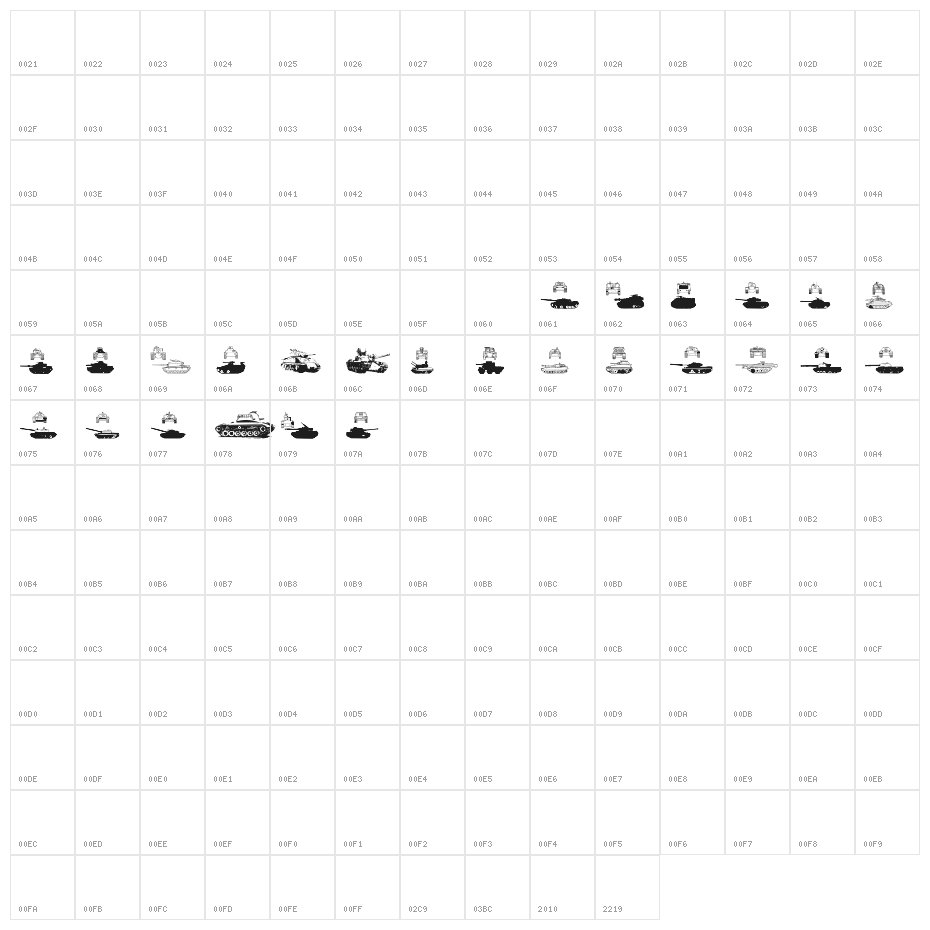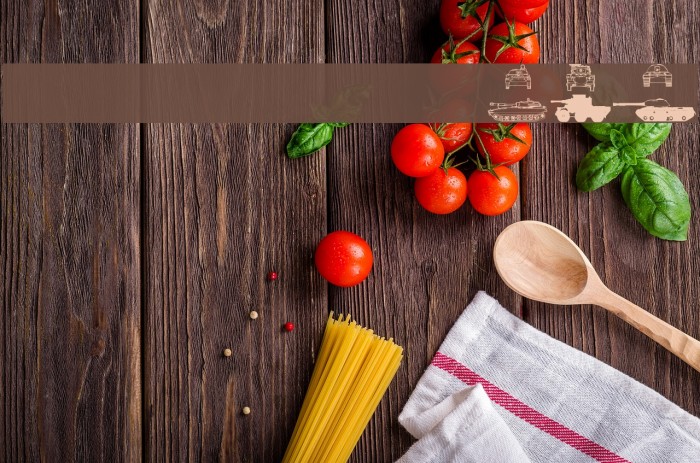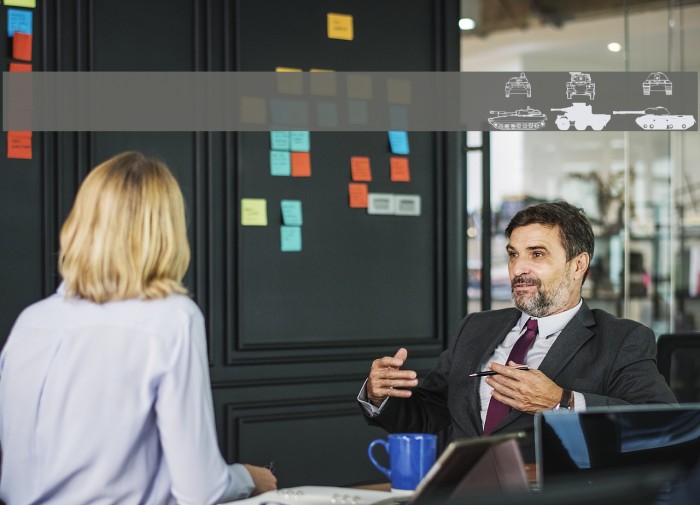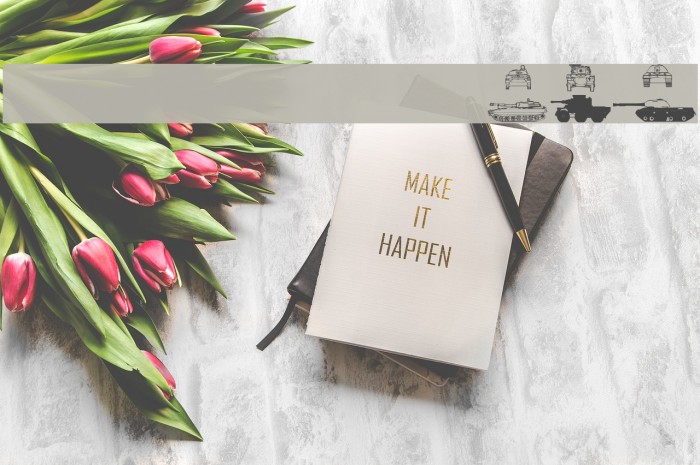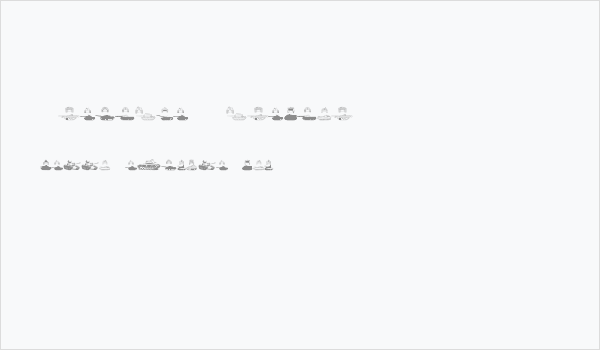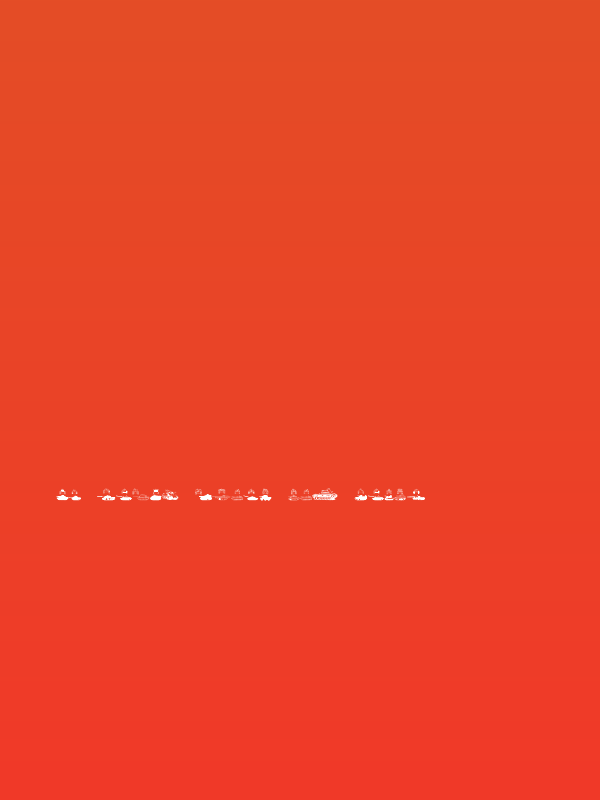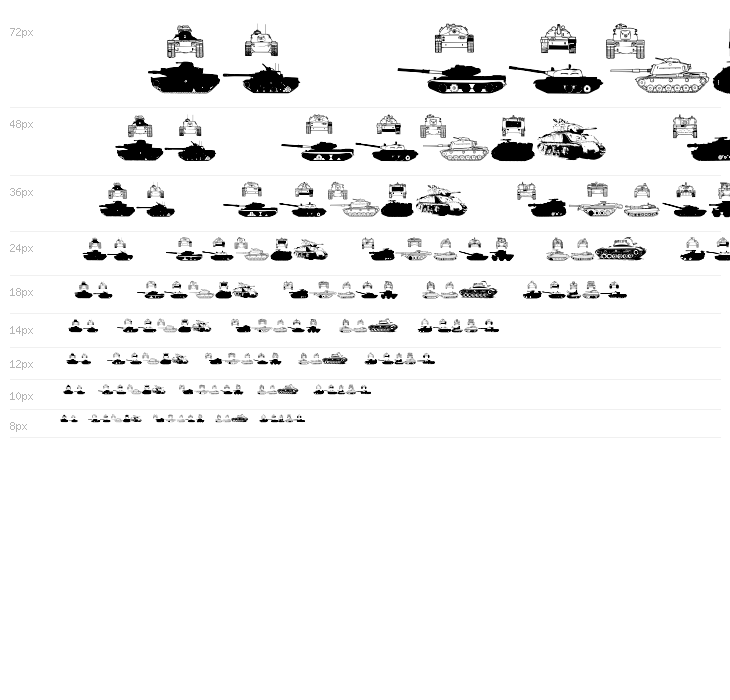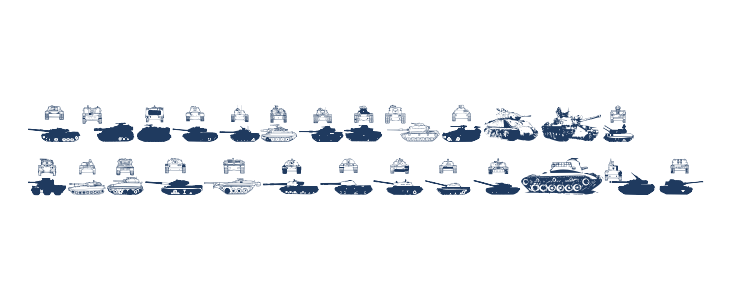
AFV2 Font
| Gesamtstil | Decorative, Thematic |
| Anwendungsfall | Icons, Themed graphics, Decorative elements |
| Vorgeschlagene Projekte | Military-themed posters, educational materials, wargaming resources, graphic design for history books, themed event invitations. |